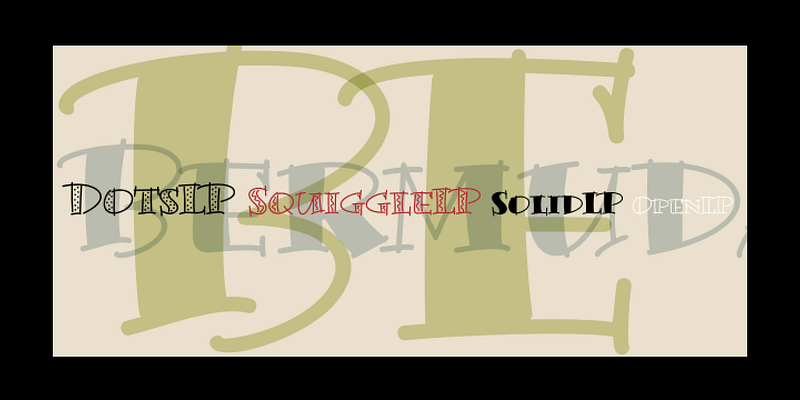
LetterPerfect ist ein Boutique-Schriftanbieter, der eine vielfältige Auswahl an Designs führt – von historisch abgeleiteten Stilen bis hin zu lebendigen zeitgenössischen Schriften. Seit 1986 ist er eine Quelle einzigartiger Schriftenlösungen für Print- und E‑Medien. Viele LP‑Designs – Spring, Wendy, Florens, Longhand – sind aufgrund ihrer Verbreitung in der Werbung vertraut.